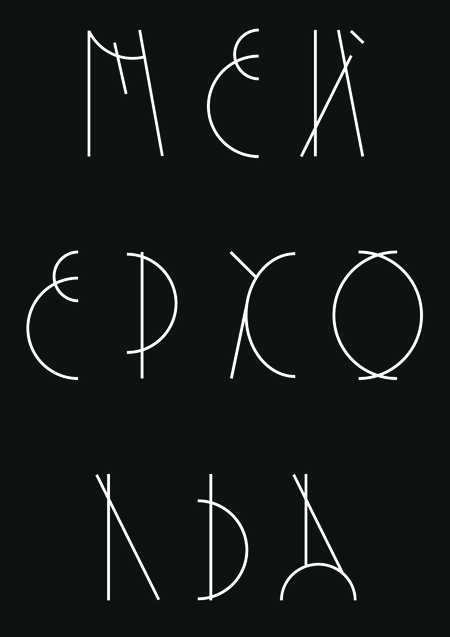
MEYERHOLD FONT
Шрифт посвящен театральным этюдам В. Мейерхольда, в которых много геометричности, движения и конструктивизма
Айдентика для фестиваля театральных этюдов конструктивизма «Антракт»
«Актер должен переживать в первую очередь форму, а не эмоции» Всеволод Мейерхольд